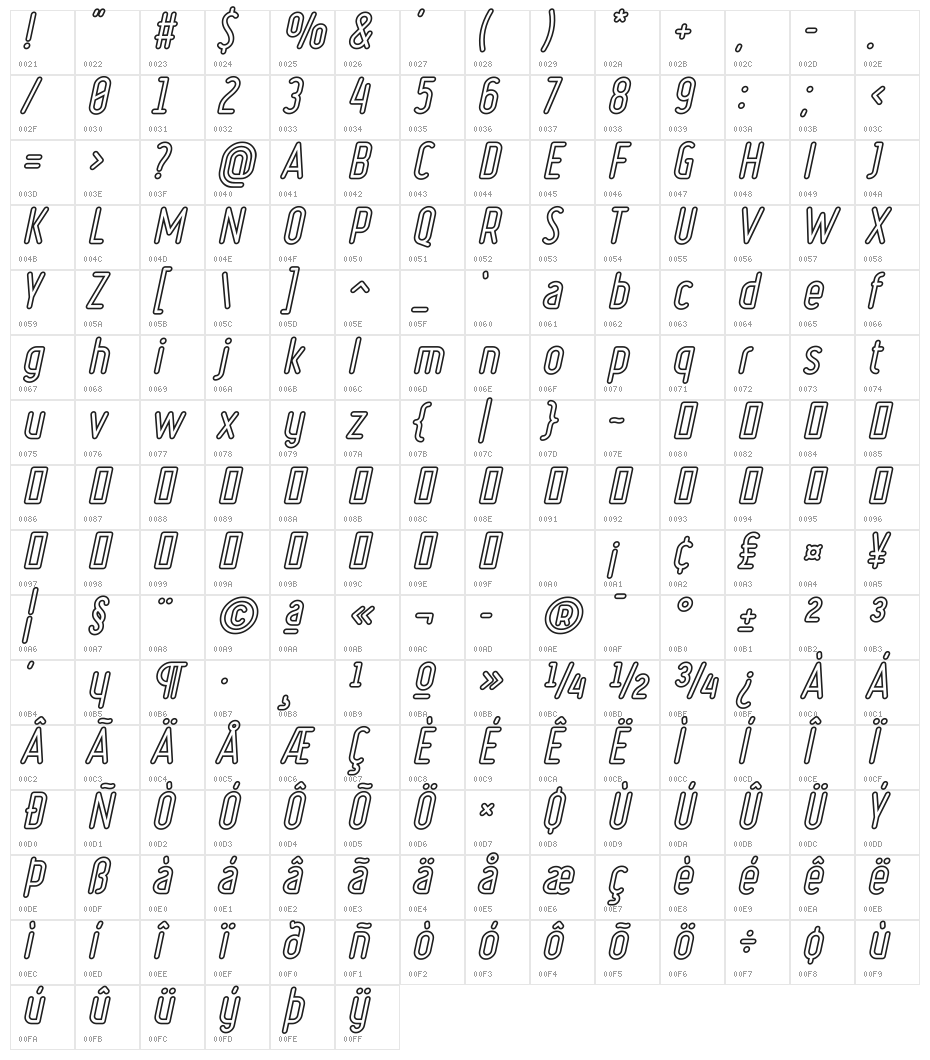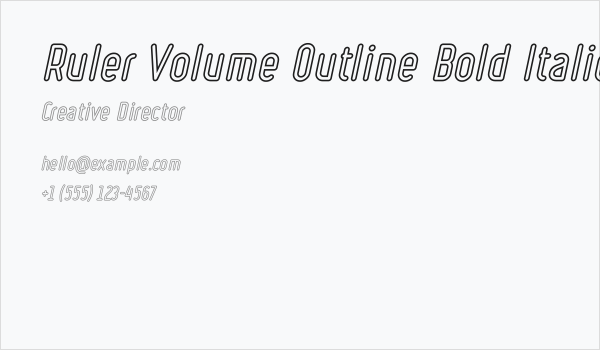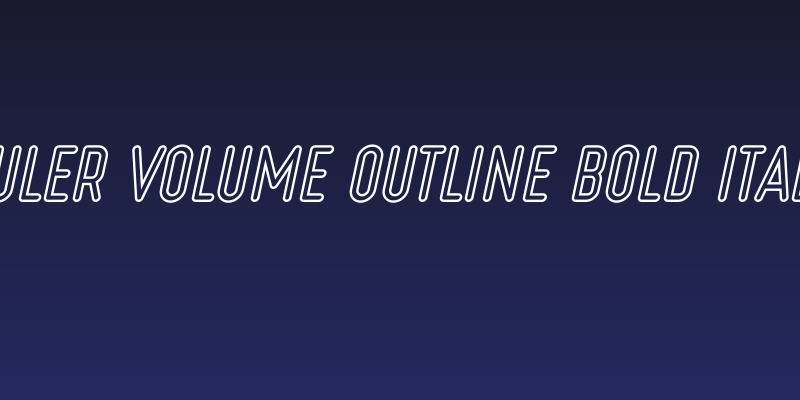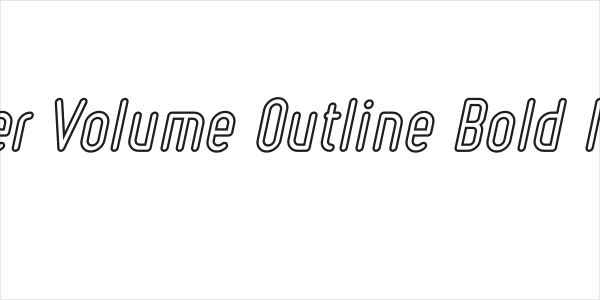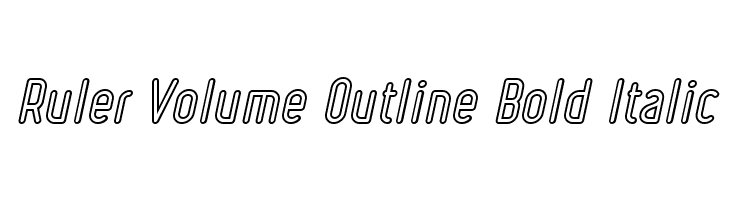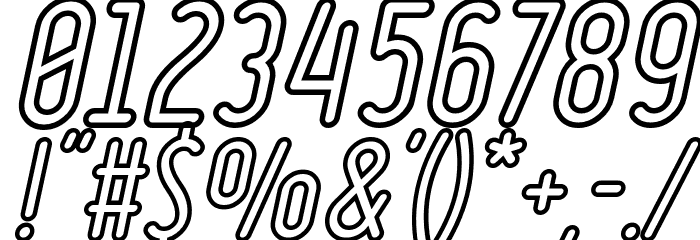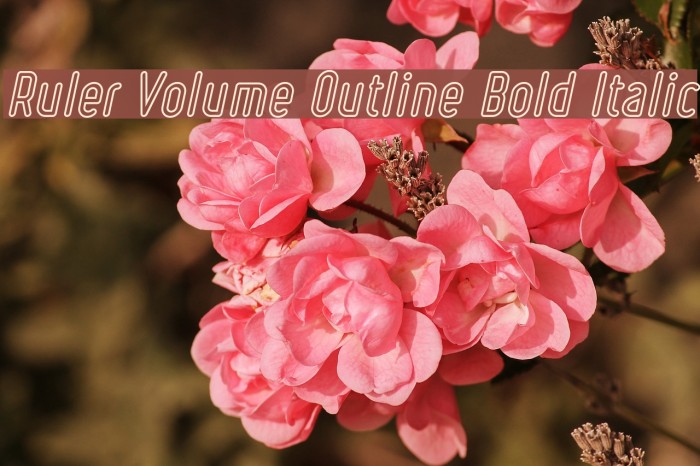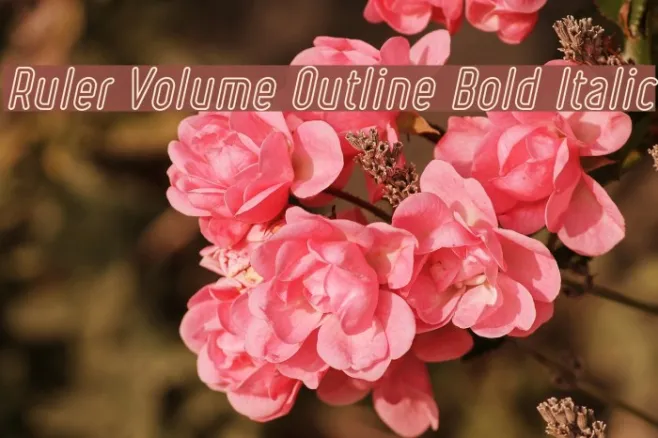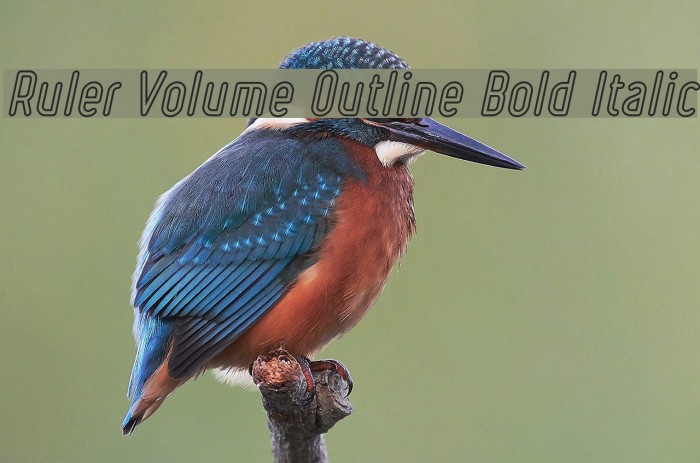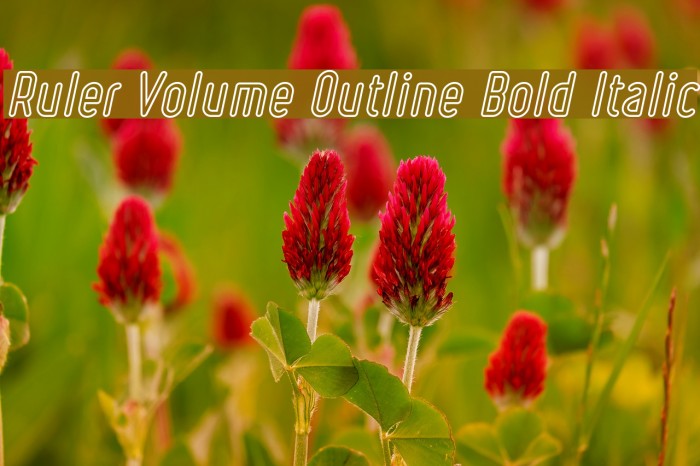
Ruler Volume Outline Bold Italic Font
| Proyectos propuestos | Ideal for headlines, posters, branding materials, and any design that requires a striking and modern typeface. |